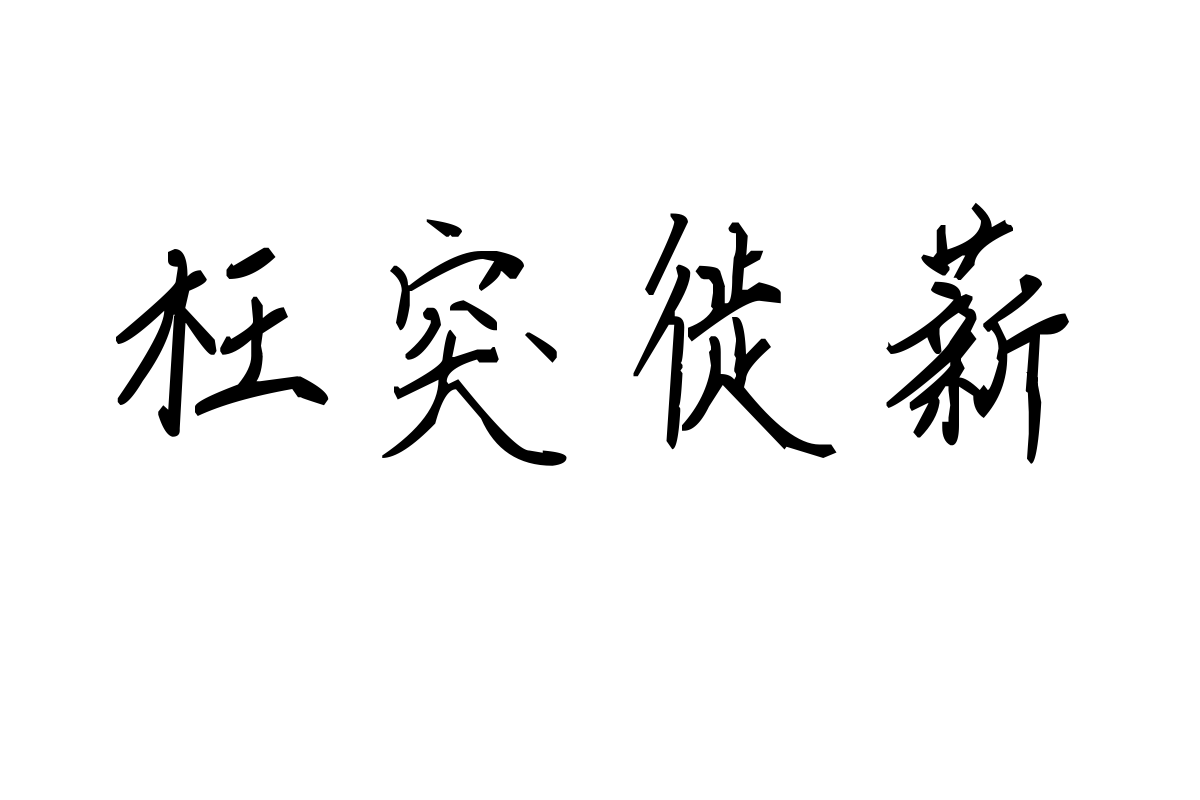
米开水墨丹青体是一种书法字体,由著名书法家米开朗基罗·博那多创作。这种字体以其独特而优美的线条和结构而闻名,给人一种古朴而优雅的感觉。
米开水墨丹青体的笔画流畅而有力,线条粗细变化丰富,既有刚劲有力的线条,也有柔美细腻的笔触。这种字体的结构紧凑而严谨,每个字都经过精心设计,使得整个作品呈现出一种和谐而统一的效果。
此外,米开水墨丹青体还具有很强的艺术性和表现力,能够很好地表达出作者的情感和意境。无论是书写古诗文还是现代文字,都能够展现出独特的魅力和韵味。
总之,米开水墨丹青体是一种非常独特且具有很高艺术价值的书法字体,深受广大书法爱好者的喜爱和追捧。